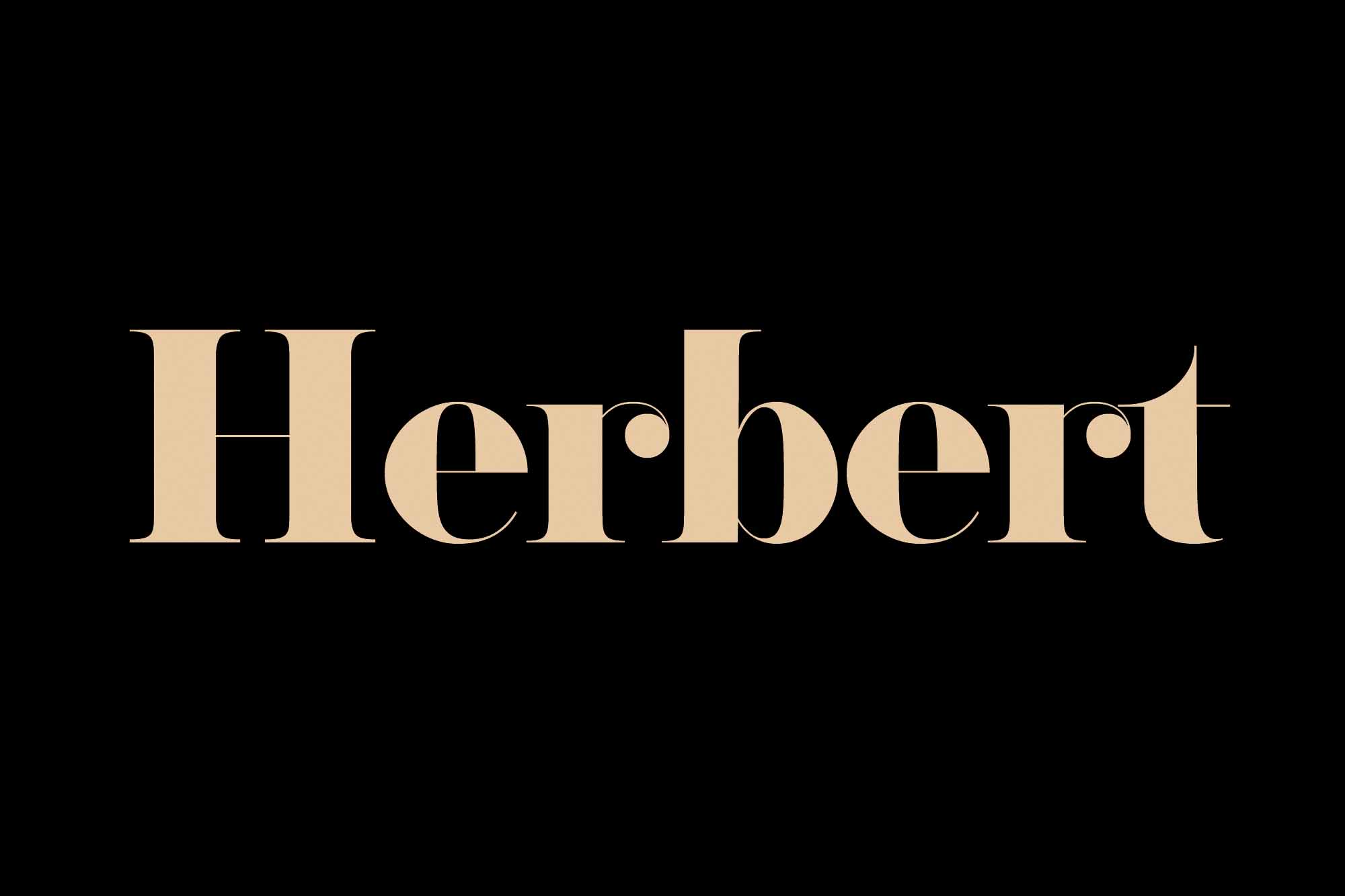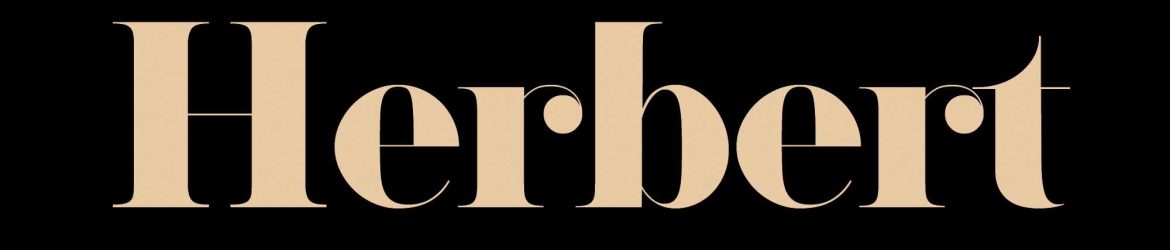
A fonte de tipo Herbert é uma opção perfeita para quem busca um toque de elegância e ressenho nas criações digitais. Inspirada no gótico, Herbert traz uma visão arcaica dos fontes de tipo Didone, desenvolvido pelo designer Danilo De Marco para o K95 Communication Studio. A característica mais marcante de Herbert é a forte contraste entre os rodos grossos e finos, criando uma sensação de robustez e elegância. Embora o design da fonte não seja ideal para uso em longas sequências de texto devido ao comprometimento da legibilidade em tamanhos menores, isso a torna perfeitamente adequada para o uso em cabeçalhos e composições gráficas que exigem uma menor quantidade de conteúdo, como marcas de marca, posters e sinalizações. Herbert é um recurso ideal para quem busca adicionar um toque de classe aos seus materiais digitais.